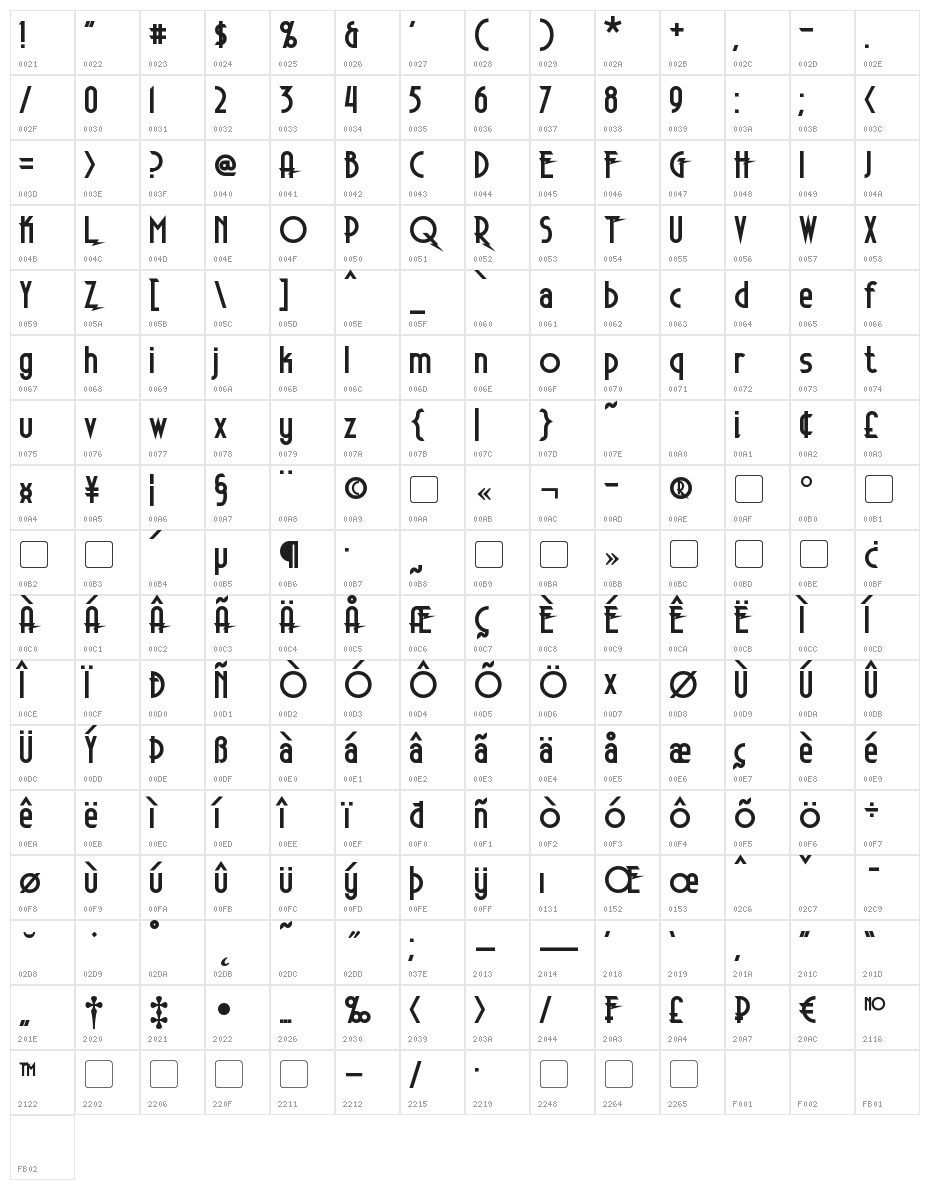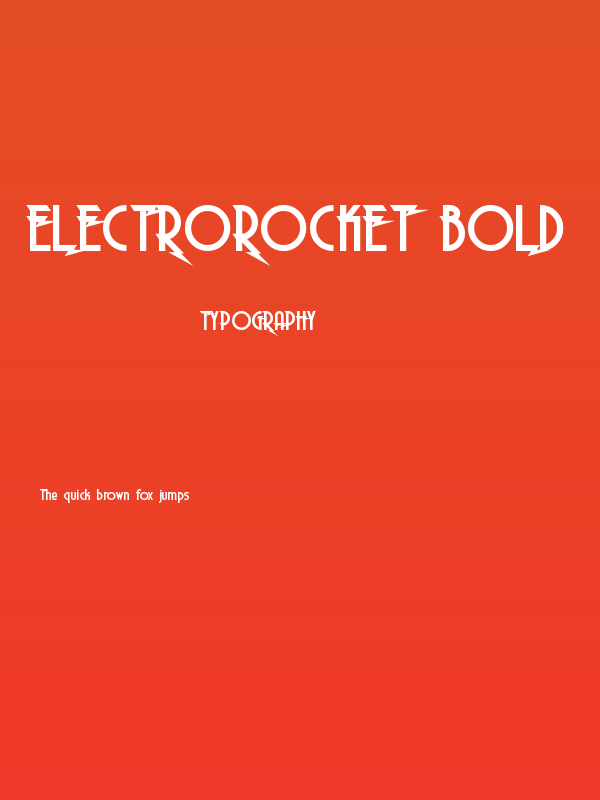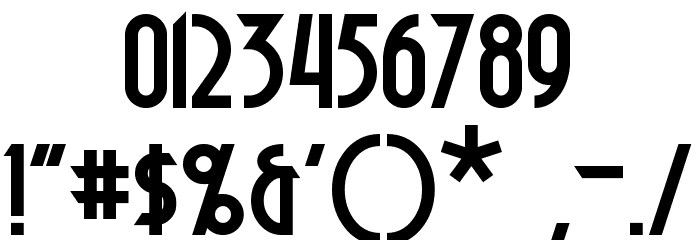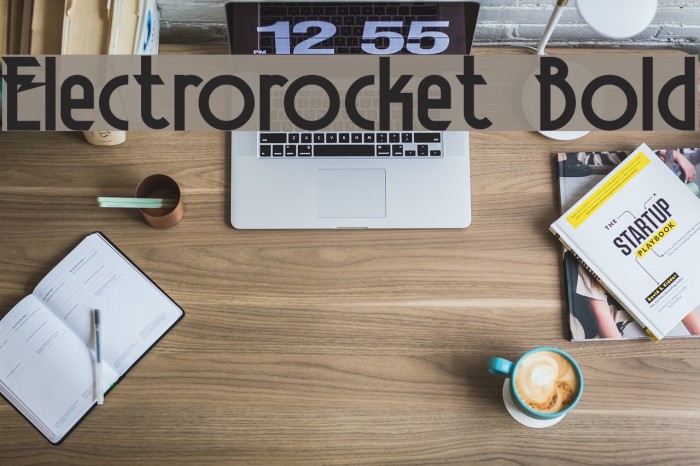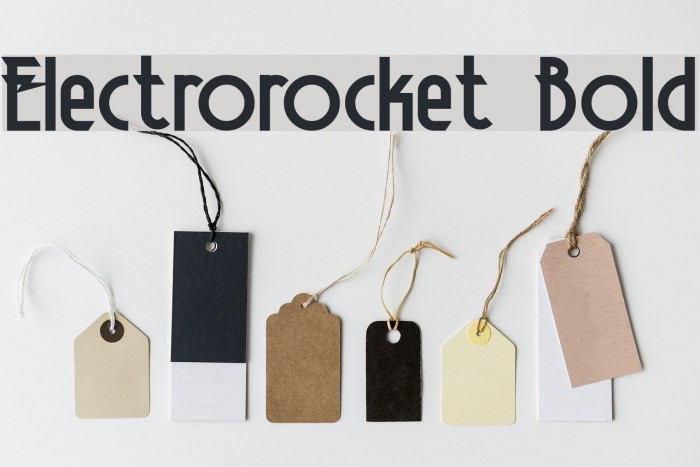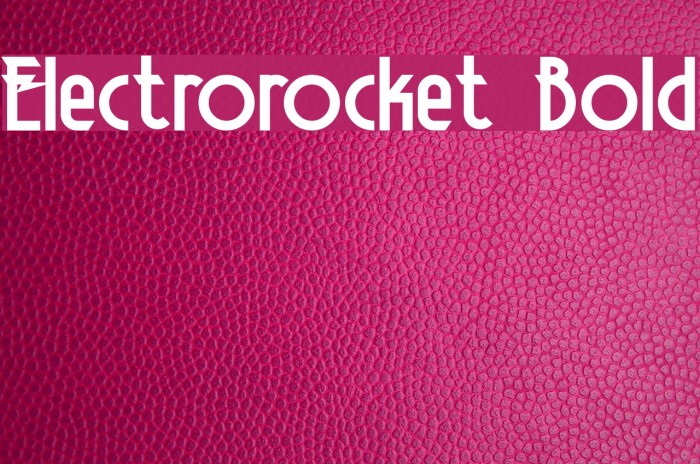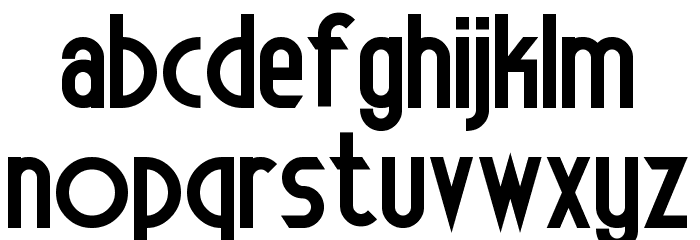
Electrorocket Bold Font
| مشاريع مقترحة | Ideal for sci-fi movie posters, tech company logos, video game titles, and any project needing a modern, dynamic look. |